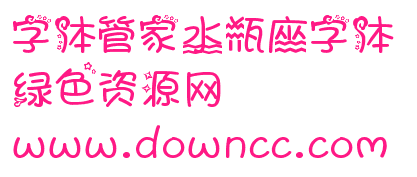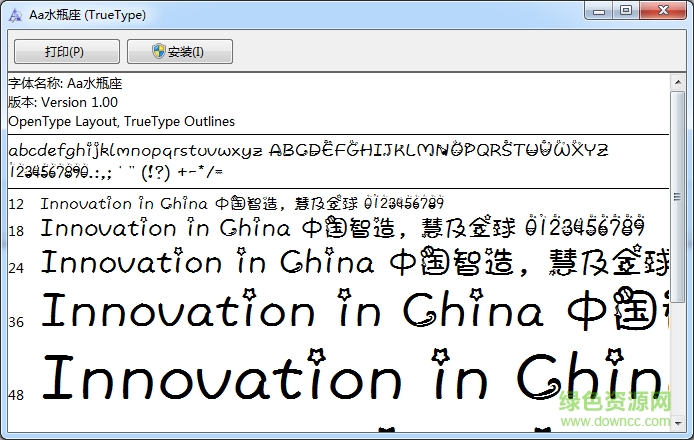
字體管家水瓶座字體
aa水瓶座字體字體管家星座系列的第二款字體,添加了水瓶、波浪、星星燈點(diǎn)綴,很符合水瓶座的溫柔和百變,更增時(shí)尚氣息,如果你也喜歡,來(lái)綠色資源網(wǎng)即可免費(fèi)嘗試哦!
水瓶座字體介紹
字體管家水瓶座,也叫作Aa水瓶座字體,是字體管家設(shè)計(jì)團(tuán)隊(duì)十二星座系列字體之一,字形呈卡通風(fēng)格,帶有星星圖案,結(jié)合了pop字體藝術(shù)字體的風(fēng)格,可以海報(bào)設(shè)計(jì)、平面設(shè)計(jì)、廣告創(chuàng)意等場(chǎng)合!
字體管家水瓶座是一款以POP體為原形進(jìn)行裝飾的星座風(fēng)格個(gè)性卡通字體,字體間裝飾了與星座相關(guān)有趣的卡通圖案,趣味性十足!